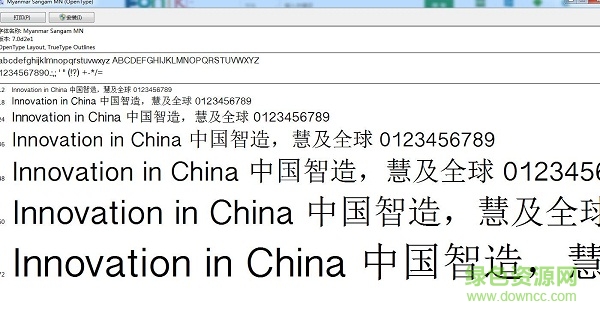
myanmarsangammn字體是緬甸蘋果OS X系統(tǒng)里自帶的無襯線字體,支持基本拉丁文和緬甸文的輸入,字面干凈大氣,線條骨絡(luò)分明,閱讀效果十分清晰,需要的朋友歡迎免費下載!
緬甸語是緬甸的官方語言,屬漢藏語系藏緬語族緬語支。主要分布于伊洛瓦底江流域和三角洲地區(qū)。使用人口約2800萬,在泰國、孟加拉、美國等也有少量分布。
緬甸文屬于婆羅米系的字母文字,其書寫特征是呈圓形,共有33個輔音字母,與元音拼合后,組成音節(jié)。緬語有四個聲調(diào),分別是:高平、高降、低平和短促調(diào)。緬語以仰光音為標(biāo)準音。